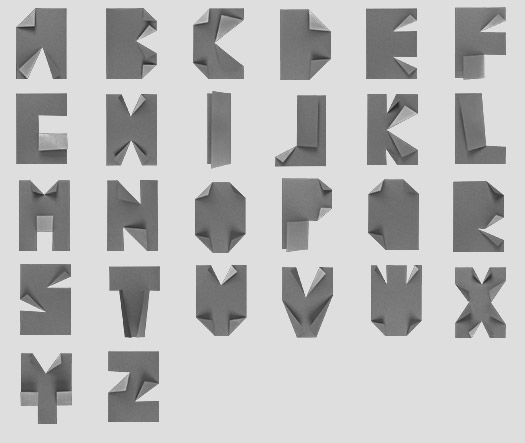
Desde Microsiervos nos avisan de las fuentes de éste estudio estonio pero, ¡oh! sorpresa, no son fuentes, son archivos .PSD de Adobe Photoshop de manualidades tipográficas hechas con los más diversos e imaginativos materiales; algo así como los workshops de EscolaMuuu hace un par de años pero a la venta, y no veas que precios…
«Eres más malo que una fuente gratuita» les podría decir, ya que son sólo imágenes, que por cierto, se pueden descargar a baja resolución al ordenador, un poco de «remuestreo bicúbico» y «et-voilá»…Lo dicho, manualidades pero desde luego no fuentes.